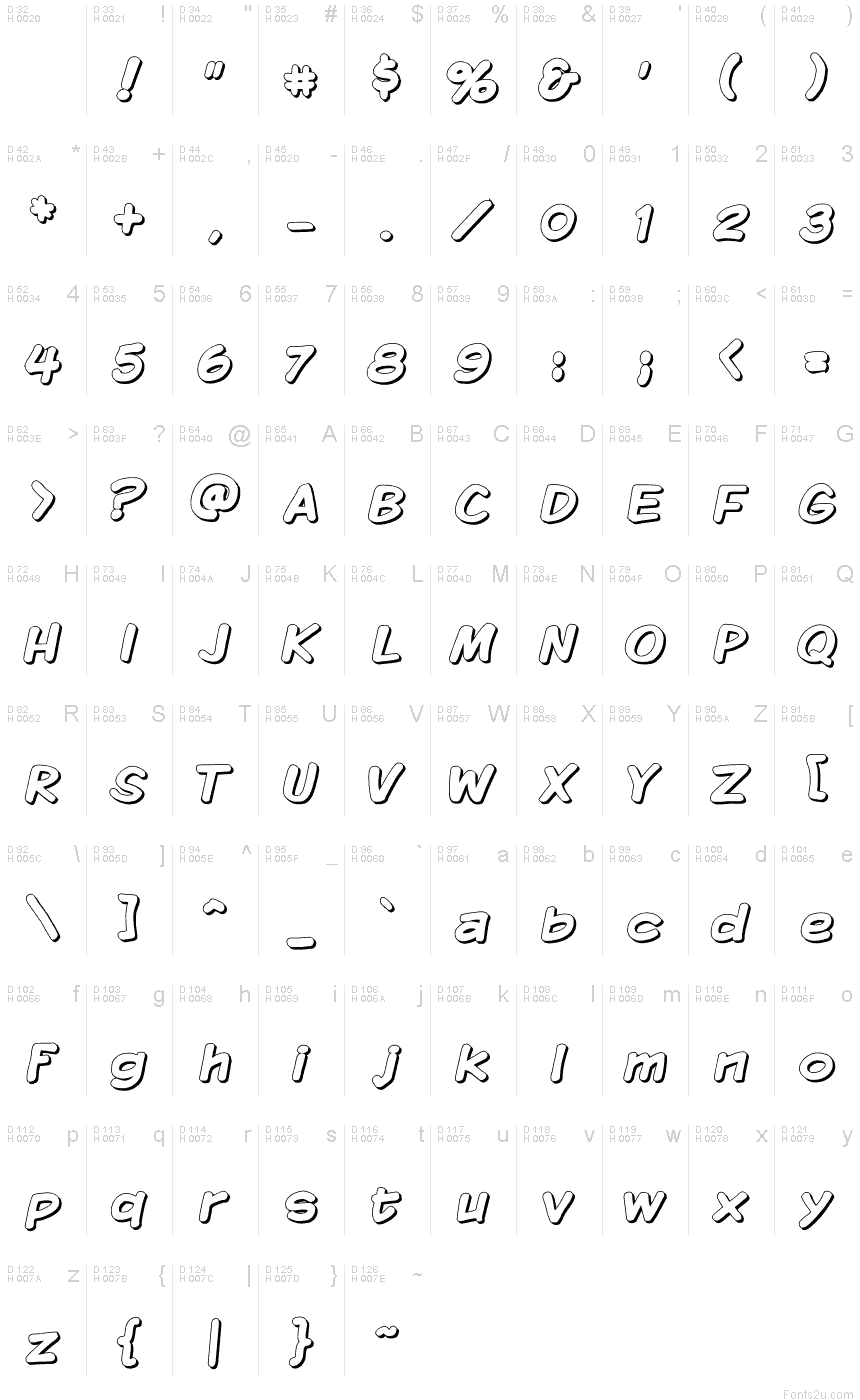
Komika Display - Shadow od Wolfbainx & Apostrophic Labs to darmowy font typu display, utrzymany w komiksowym klimacie. Dzięki pulchnym, zaokrąglonym literom i wyrazistemu czarnemu cieniowi każde słowo zyskuje wygląd naklejki – jakby tekst został przed chwilą odklejony z komiksowej strony i wklejony prosto w Twój projekt. Linie są gładkie i mięsiste, a czyste, białe wypełnienie aż prosi się o dodanie żywych kolorów, dzięki czemu nagłówki przyciągają wzrok, nie sprawiając przy tym wrażenia ciężkich czy sztywnych.
Dzięki Komika Display - Shadow Twoje tytuły od razu stają się zabawne, głośne i nieco łobuzerskie. Ten darmowy font świetnie sprawdzi się na okładkach komiksów, w tytułach książek dla dzieci, miniaturkach na YouTube, opakowaniach przekąsek, ulotkach czy w zabawnych logotypach. Używaj go w dużym rozmiarze, aby efekt cienia naprawdę wybrzmiał, a w tekście głównym połącz go z prostym krojem bezszeryfowym, by zrównoważyć tę rysunkową energię.